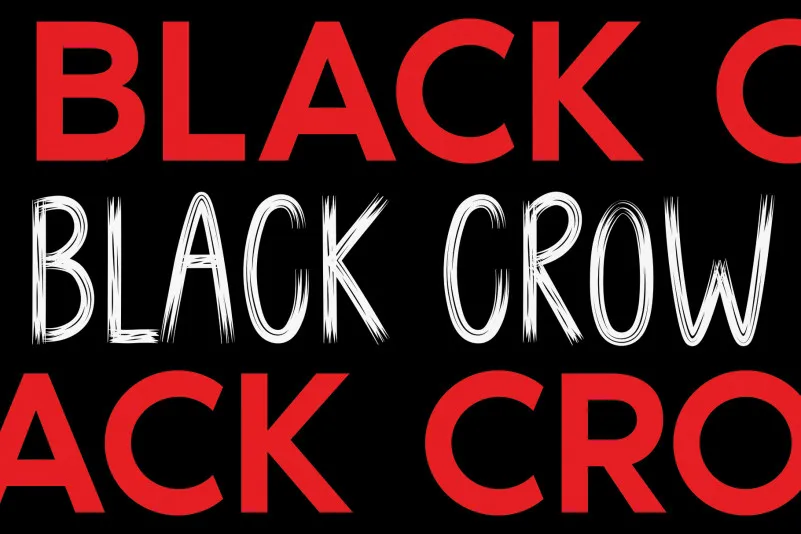
BLACK CROW Brush Font – Download Grátis
A BLACK CROW Brush Font é uma escolha perfeita para quem procura personalidade no design digital. Criada com a fina ponta de uma varinha de pintura, essa fonte impressionante e única destaca-se instantaneamente, tornando os seus trabalhos de design únicos e chamativos. Ideal tanto para gráficos profissionais quanto para projetos pessoais, BLACK CROW oferece um toque assertivo que certamente deixará sua marca na web ou em qualquer mídia digital. Inspirada no movimento vibrante da arte de pintura, esta fonte é o recurso perfeito para designers atentos à estética e aos detalhes. Experimente a diferença única desta varinha de pintura moderna e transformadora!